秀英体のコネタ
今年の目玉は、昨年の上製本実演に引き続き、DNPを支えてきた職人の技をライブでご覧いただく「匠シリーズ」第2弾、活字直彫りと校正刷りの実演でした。
今回の秀英体のコネタは、東京国際ブックフェア2006のDNPブースのもようをご報告いたします。
今年の秀英体コーナー
もちろん実演だけではありません。秀英体だって展示していました!
「ものづくりからITまでをつなぐソリューション「秀英体」」と題し、DNPオリジナル書体である秀英体の歴史や利用事例、そして新しい取組みである高精細ディスプレイ表示用書体のデモなどをご紹介いたしました。
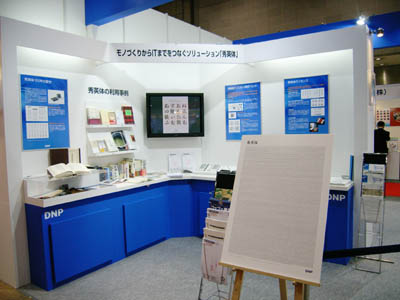
秀英体コーナー
活版時代の道具などと一緒に、秀英体研究のご紹介。実際に手にとって中をご覧頂きました。道具類は、電胎母型・彫刻母型・原図・パターンなど書体作りに関わるものや、高低見・幅見・版面見という活字の規格を計測する道具、そして短冊形活字見本帳などをご紹介しました。
活版時代の道具いろいろ
利用事例コーナーでは、秀英体をカバーや本文で使用した書籍・雑誌をご紹介。
新刊からロングセラー、辞書・全集、ファッション誌まで、いろいろなシーンで使われているんですよ。
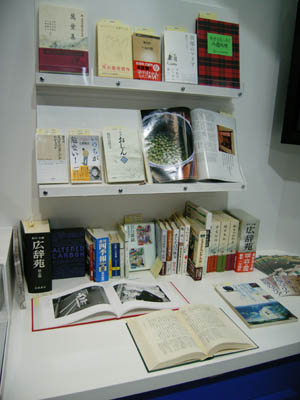
利用事例の本は、実際に手にとって比べながらご紹介
高精細ディスプレイ表示用秀英体のコーナーでは、各種携帯端末での表示例をご紹介しておりました。まだまだ表示用ではゴシック体の利用が中心ですが、デモを通していろいろな書体を比較して、秀英体の持つ表現力を感じていただけたのではないでしょうか。
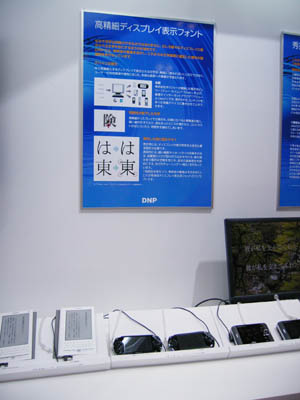
電子書籍のヘビーユーザーの方にもご覧頂きました
今年は秀英体ポスターも作りました。秀英体の豊富な字種から、23,500字を並べたポスターです。ご希望の方にお配りしておりました。お部屋に飾って頂けているでしょうか。
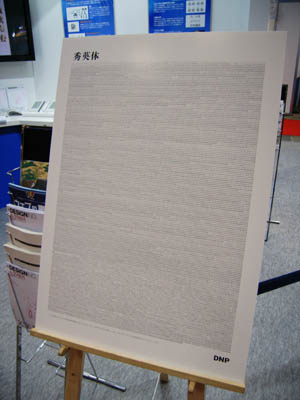
最後のほうは見たことのない謎の字だらけです
実演:活字直彫り
昨年は上製本づくり、今年は金属活版印刷の工程から、活字直彫りとゲラ刷りをご紹介です。
活字直彫り(地金彫り/新刻とも)とは、活字の材料である鉛の棒に、直接、手で文字を彫っていく作業のことです。
通常、金属活字は鋳造してできあがります。保有するすべての文字は「母型」と呼ばれる文字の型があり、そこに溶けた鉛を流し込んでつくられます。しかし、特殊な漢字や記号など、型のない文字がまれに原稿に含まれていることがあります。その文字が今後何度も使われることが想定されれば、母型を新たに作ります。しかし母型づくりは 文字を手作業でレタリング→亜鉛の腐食版を作成→彫刻機で母型を彫刻 という手順で作るため、少し時間がかかります。印刷現場は常に時間との戦い。特に雑誌は入稿から印刷へまわすまでのスケジュールが非常に短い事態がままあります。母型を待っている時間がない、そんなとき、手作業の活字彫刻の出番です。
実演する職人は中川原勝雄さん。DNP市谷工場で約30年あまり、活字直彫りを一手に引き受けてきました。
中川原勝雄さん、文字を彫るスペシャリストです。
それでは、作業の工程を見ていきましょう。
実演では本文で一般的に使用される9ポイントの明朝体「銀」を彫っていただきました。
作業は6工程に分かれます。すべて小さな活字を彫る作業のため、どれだけ近寄ってもなかなか見えません。そこで、手元をCCDカメラで撮影し、中川原さんの上部に取り付けた大きなモニターで文字面の状況をライブでご覧頂きました。
実演中の中川原さん。手元はモニターで。
(1)下書き
まっさらの鉛の棒に、コンパスの針の先端で、文字の輪郭のアタリをつけていく作業が「下書き」です。深くは彫らず、ひっかく程度の力で作業をします。
(2)字入れ
直角の「定規」を使い、文字の直線部分をしっかりと刻む作業が「字入れ」です。この定規、L字型に折れた金属になっており、中央に溝があります。L字の直角部分に活字を当て、定規の溝にコンパスの脚を滑らせてもう一方の脚で直線をしっかりと刻みます。
字入れ作業。活字と爪の大きさを比べてください。こんな小さいところに文字を彫りますよ!
中央に溝の入っている金属が「定規」です。直角部分に鉛を指で固定しています。
(3)浮き出し
文字通り、文字の輪郭の外側を彫り、文字部分を浮き立たせる作業が「浮き出し」です。
(4)粗彫り(彫り下げ)
文字の面にならない、不要な部分をどんどん彫り進める作業が「粗彫り」です。
大きなサイズの活字になると、どうしても不要部分が増えるため、粗彫りの作業に時間がかかってしまうそうです。
彫刻の作業は、はたから見ていると彫刻刀を動かしているだけにしか見えません。各工程で比較すると、下の写真のようになっています。
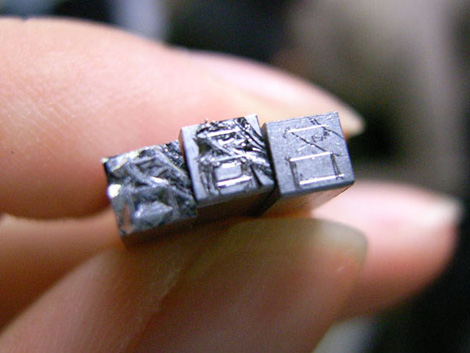
右から字入れ後、浮き出し後、粗彫り後。
字入れ後の文字は、縦・横の線は、定規を使って直線が引かれています。斜めの線は、下書きの時に入れた毛書きの線のみです。
浮き出し後には、文字の輪郭の外側だけを彫り、文字が浮き出ているのがわかります。
そして粗彫り後、隅など文字の線がこない空白の部分まで彫られています。残った部分だけが、印刷されることになります。
(5)仕上げ彫り
文字の輪郭を整える作業が「仕上げ彫り」です。秀英体のほっそりしたハライの曲線、ハネ、ウロコ……印刷される文字がこの作業で生まれます。ほんの小さな字ですので、わずかな角度、わずかな手の動きがそのまま製品に直結します。
中川原さんは今でも、仕上げ彫りの際には緊張する、と言います。
(6)仕上げ磨き
彫り終えた活字は、文字の面に(1)下書き で入れた線が残っています。そのため、とても目の細かい砥石で表面を2度ほど撫でるように磨いて、この線を消します。しつこく磨いては、活字の高さが低くなるので厳禁です。
「マス」に活字をセットし、砥石で磨きます
これで活字の新刻が完成しました。かかる時間はわずか15分ほど。
新刻した活字は、最後の磨きのおかげで、鋳造活字とは異なり、活字の面がぴかぴかと輝いています。
作業には、さまざまな道具が用いられます。
道具の数々。これらを駆使して活字を彫っていきます。
彫刻刀
まずは何といっても彫刻刀です。
作業工程ごとに分かれているだけでなく、活字のサイズによっても刃を使い分けるそうで、数十本という刃が用意されているそうです。削る対象は金属ですので、刃先のメンテナンスは欠かせません。
ゴム印用の印刀を買ってきて、自分仕様に研ぎなおします。刃先にも独自の工夫があり、側面でも彫れるになっています。通常は一方向のみに動かすものですが、中川原さんの彫刻刀は押しても引いても彫れるようになっています。
かつては、よりよい印刀にするべく、いいと聞いた焼き入れの方法をいろいろ試したそうです。噂という噂はみんな試し、果ては「大根に挿しておくといい」というものまで。でも「刃物づくりはとても大変! うまくいかなかった」とのことです。
中川原さんの彫刻刀。右から仕上げ用、浮きだし用、荒彫り用(彫り下げ)。
台
彫刻作業でひときわ目を引くのが、手を乗せる台です。
木で出来ており、T字型に組み合わせてあります。特に名称はなく、「台」と呼んでいるそう。中川原さんの体のサイズに合わせて大工さんにオーダーメイドしたのだそうです。
手に合った台が作業には欠かせません。
写真のように手を置きます。右手は手首を台に載せ、左手は指先で活字を押さえ、手のひらで台を包むようにします。
置き方ひとつとっても、その職人によって少しずつ異なっているそうです。
手の置き方はこうです。
台は脚の先に板を挟み、わずかに傾斜をつけて作業します。
なぜかというと、彫刻作業は台のそばにライトをつけて作業するため、活字面に影がかからないように傾けているのだそうです。
先端に板を挟み、台を傾けています。
ルーペ
彫る際にはルーペも必需品です。台にセットし、彫刻中は常にルーペをのぞきこんで作業します。高さ・向きなど調整できるようになっています。レンズは小さいながら厚みが18ミリもあります。ぴたりと焦点が合うと、ものすごくクリアに拡大されます。
中川原さんのこのルーペは以前から使っていたものですが、現在でも彫金など細かい作業で使われるスタンドルーペと形が似ています。
脚は2ヶ所曲がるようになっており、角度や高さを変えます。
コンパス
下書きをしたり字入れをするために使うのがコンパスです。製図用ではなく、これもルーペ同様に工芸用工具として販売されているスプリングコンパスと同じ形です。
ずいぶん脚が短いですが、これは使っているうちにどんどん削れてこの短さになってしまったとのこと。
本当はもっと脚が長かったのだそう。
定規
定規といっても、目盛りはついていません。L字型の金属の中央に溝があるだけです。溝引きの要領で用います。L字の直角部分に鉛を指で固定し、溝にコンパスの一方の脚を滑らせると、残りの脚が平行な線を引いてくれる、という仕組みです。
シンプルな道具ながら、直線を引くための必須アイテムです
マス
仕上げ磨きで使う道具がマスです。中央が四角に空いています。この中に彫り終えた活字をマスの表面と活字の面を同じ高さにセットし、ネジで固定します。そしてマスごと仕上げ砥ですーっと磨きます。マスは活字より硬い金属で出来ているため、一緒に磨いても活字の表面だけが削れます。
小さいながら手に持つとずっしりと見た目以上に重みがあります。
ネジが3方向についているのは、活字をぎゅっと固定するためです。和文であれば中心のネジだけでいいのですが、欧文、とくにイタリック体だったり、ベースラインからはみでているような活字のボディが水平垂直ではない文字の場合、3方向のネジで固定する必要があるそうです。
ネジが1つの和文用も中川原さんはお持ちでした
活字
そして文字を彫る鉛活字。もちろん面は平らな正方形です。
ここに彫っていきます
中川原さんのこと
中川原勝雄さんは、昭和9年生まれ。中学卒業後、地元青森で彫師の庭田与一さんに弟子入りし、活字を彫るという仕事につきます。お師匠である庭田さんは、岩田母型(現イワタ)の種字彫刻を行なっていた馬場政吉さんの弟子にあたり、中川原さんも馬場流といえるでしょう。馬場さんについては、大日本スクリーンのサイトで連載されていた小宮山博史さんによる「書体の背景 第7回 無名無冠の種字彫り師」に詳しく紹介されています。
イラストルポライターの内澤旬子さん。
『秀英体研究』の著者である朗文堂・片塩二朗さんも中川原さんに質問。展示していた『秀英体研究』を開きながらお話なさっています。
「ものすごく詳しい人だったから緊張したよ~」とは中川原さん談。
かなり専門的な話になっています
彫刻の方法について、具体的な質問も頂きました。ひとつひとつ、中川原さんが丁寧に解答します。
質問に答える中川原さん。真剣です。
彫った活字を直接手にとってご覧頂くと、彫り跡も生々しく、これを本当に手が彫ったんだ! とあらためて驚いてしまいます。
彫った人と彫った活字、両方が目の前に
さて、実演はこれだけではありません。彫った活字はすぐさま隣の小さな印刷機に回されます。
次回のコネタは「ゲラ刷り」の実演についてご報告いたします。
- *1 中川原さんは下書きはコンパスで行なっています。昔は筆を使っていたそうですが、締切りがあまりに急ぐので、コンパスで描くようになったのだそうです。